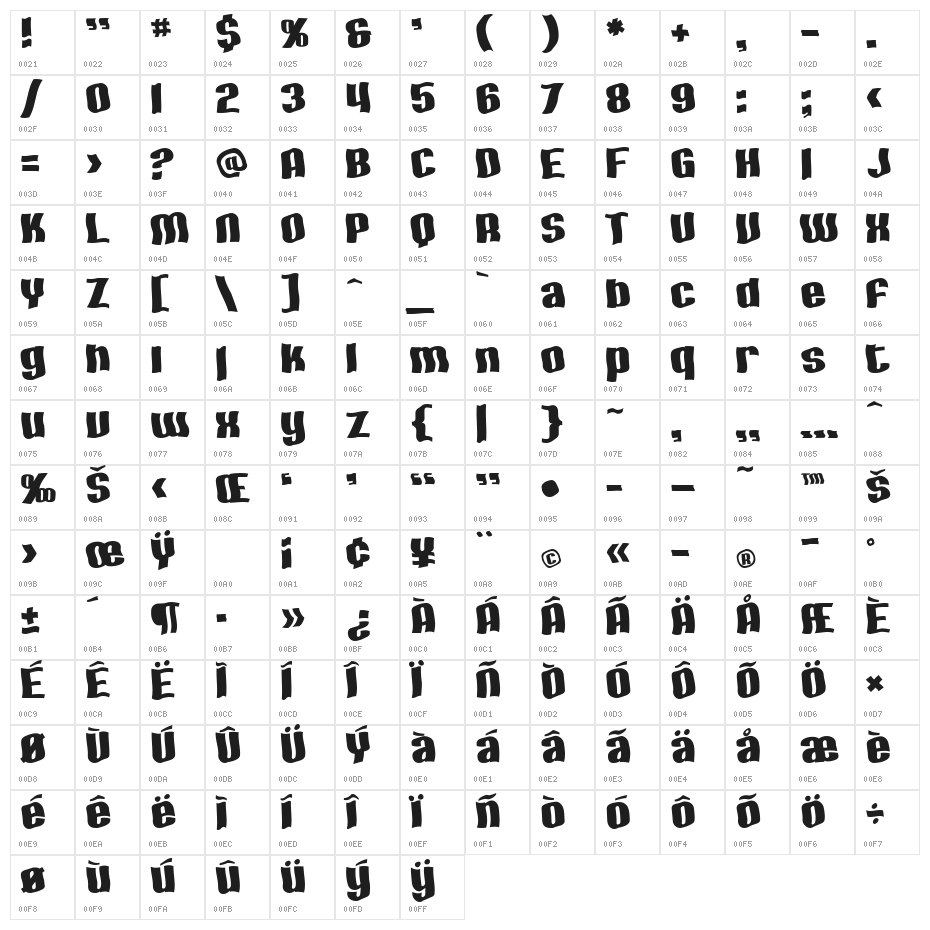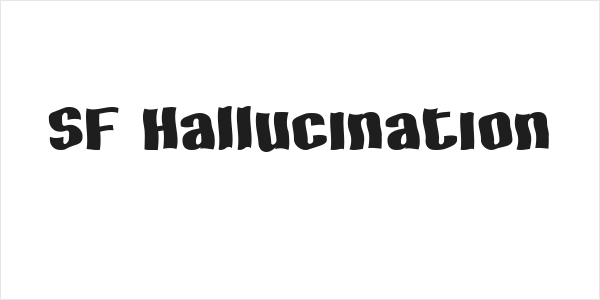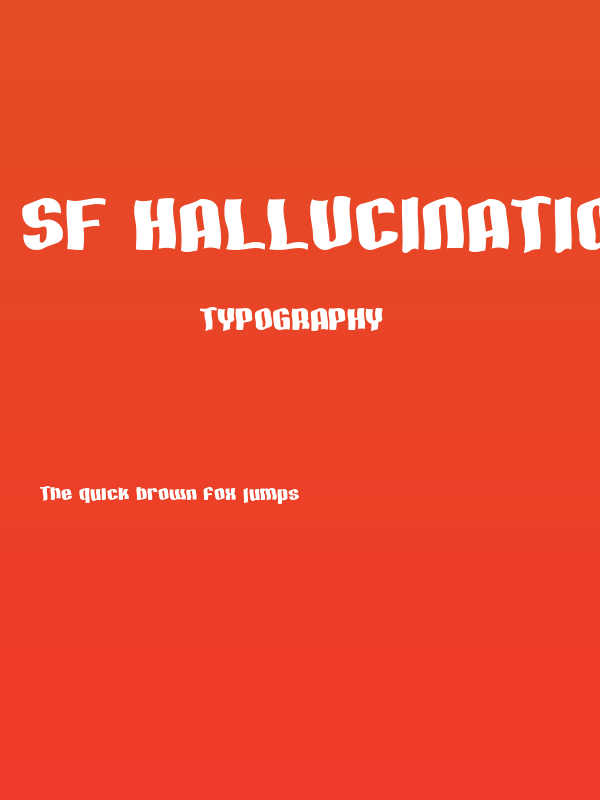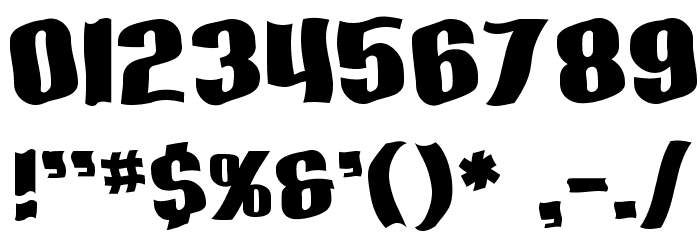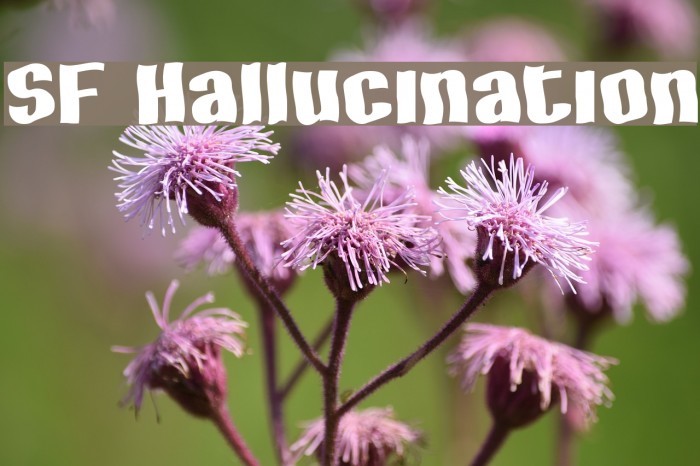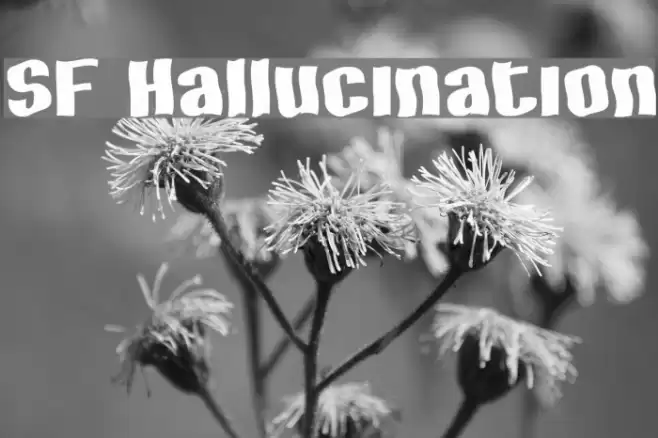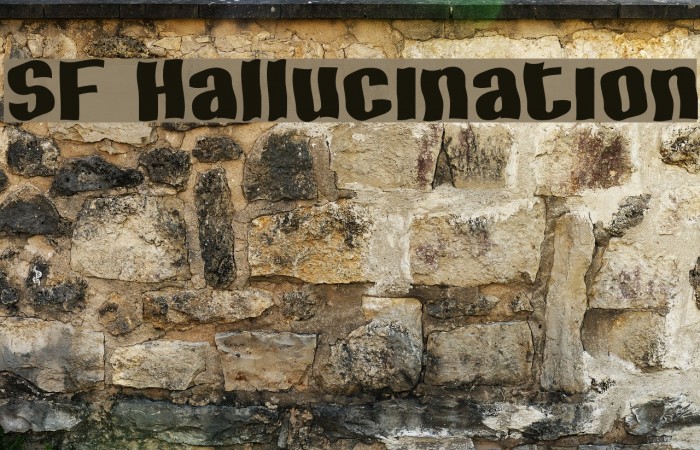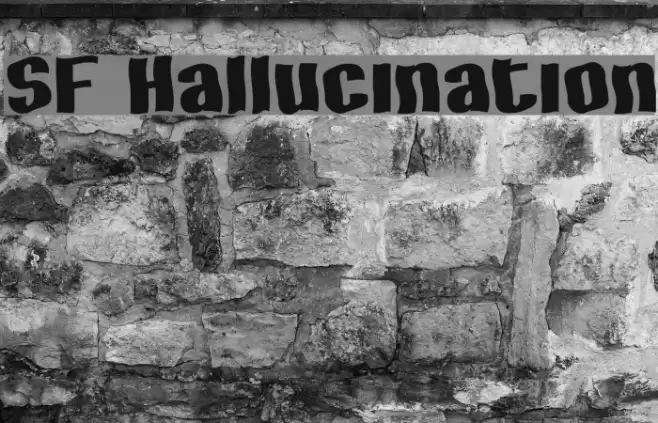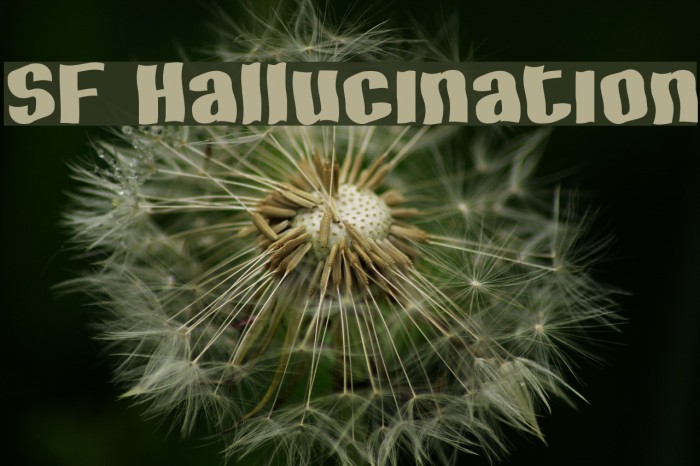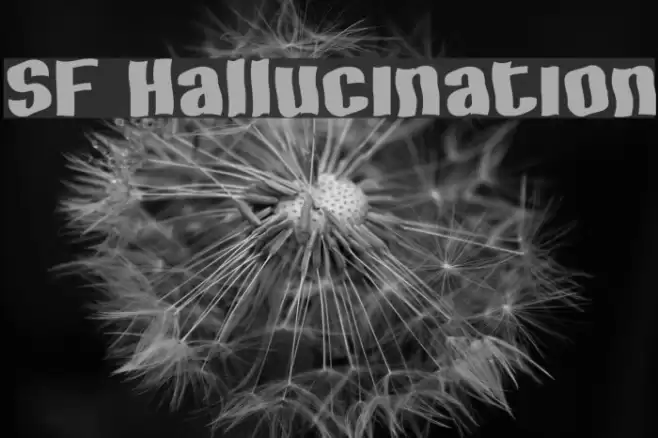
SF Hallucination Font
| Style général | Modern, Decorative |
| Projets proposés | Ideal for posters, album covers, and creative branding projects that seek to capture attention with a bold statement. |